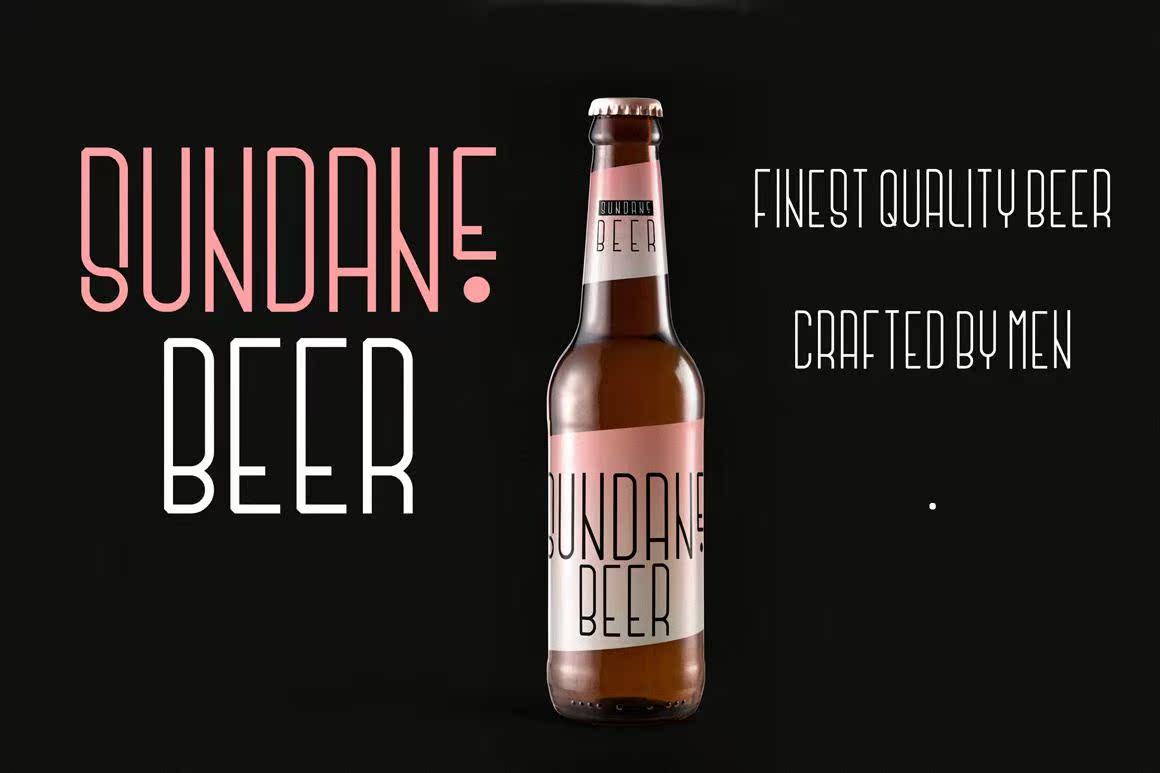
简介GargapuriAtalalTracondensedSanserifont。您可以使用ArgapuriFont创建任何全新的现代内容。该字体适用于标题、引用、徽标、Web、杂志封面、编辑设计、印刷海报、标牌、橱窗设计、,和更多。介绍Gargapuriatallalltracondensedsansserifont。您可以使用ArgapuriFont创建每一个全新的现代内容。此字体适用于标题、引用、徽标、Web、杂志封面、编辑设计、印刷海报、标牌、橱窗设计等。